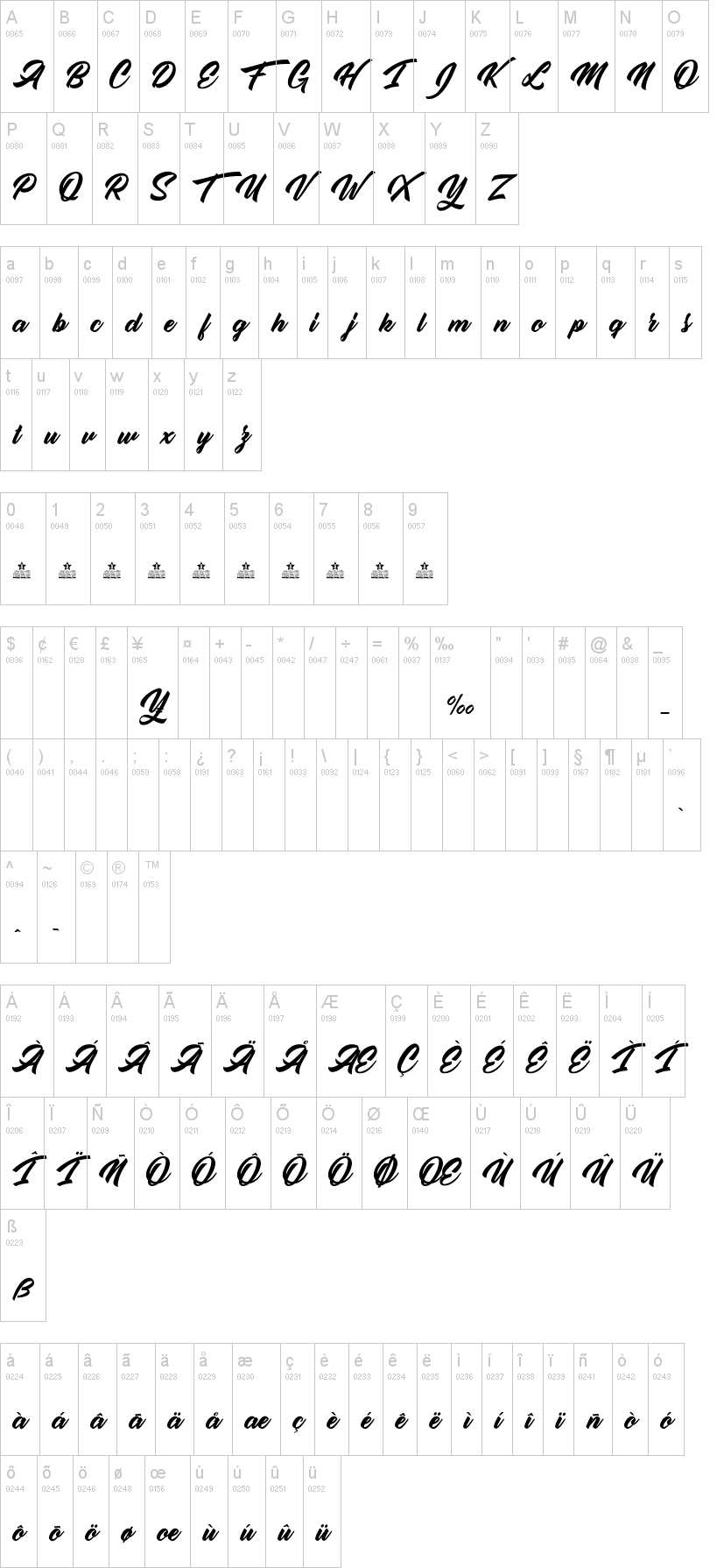
Sweet Sixteen
Sweet Sixteen 是一种英文字体,由英国设计师 Ian Brignell 在 2002 年设计,是一种比较浪漫的字体,它的字体特色是圆润的线条,具有柔和的感觉,同时还有比较深厚的立体感,可以用于商业设计,网页设计,书籍,海报等等。
Sweet Sixteen是一款非常不错的手写艺术字体,具有很好的视觉感,适合于文化类的宣传设计、商业类品牌的广告和产品包装设计以及个性化文字排版等较多场景。
Sweet Sixteen字符映射图